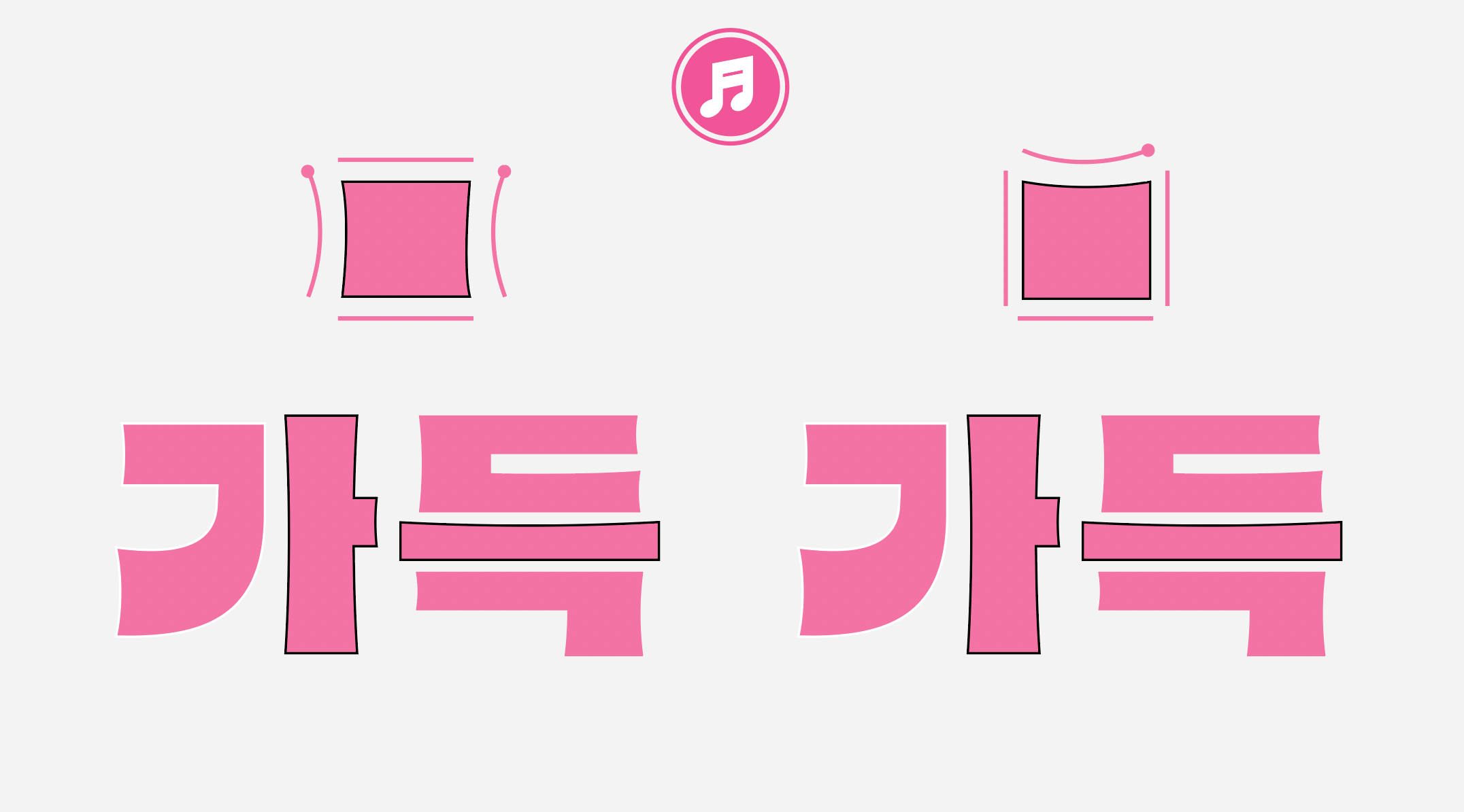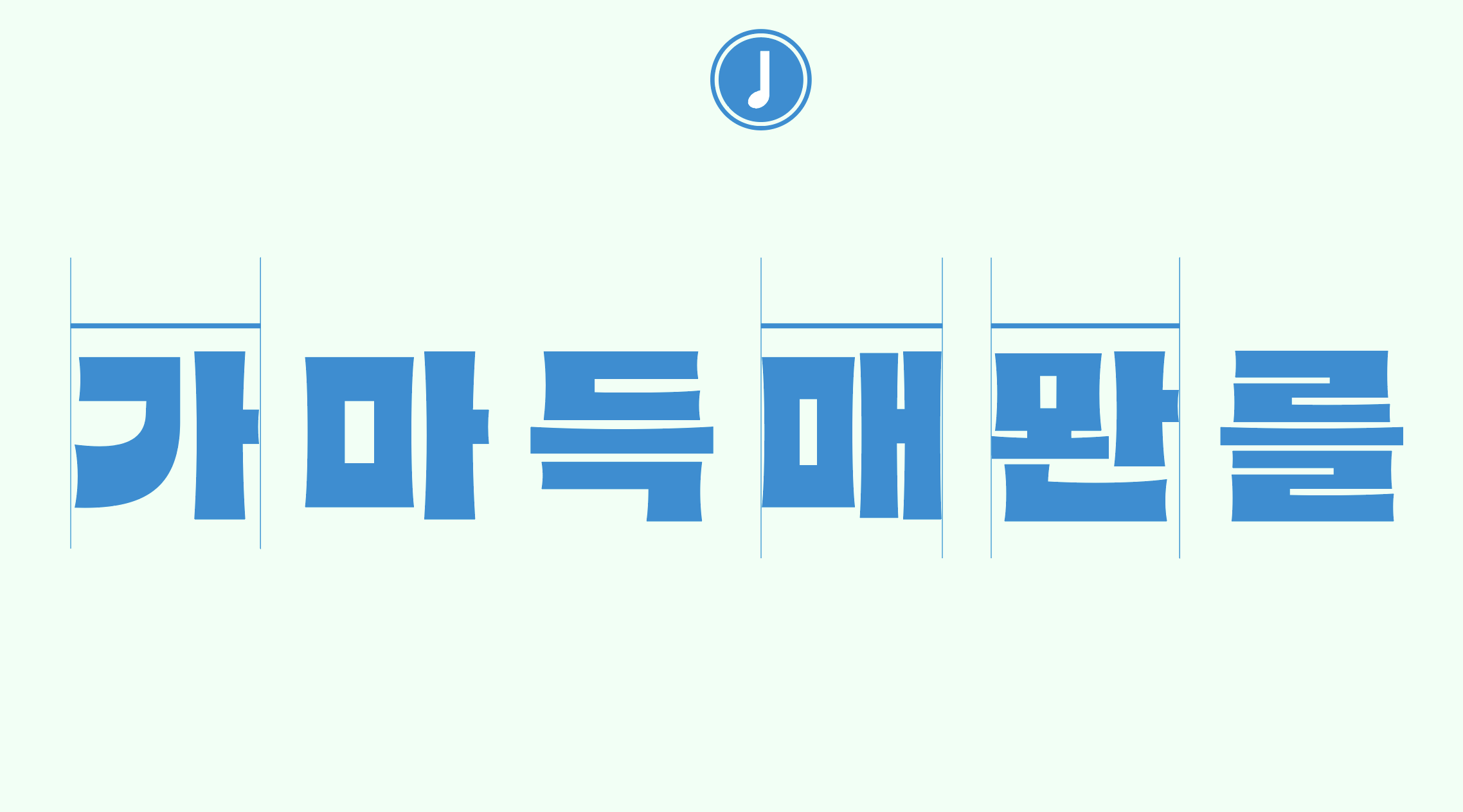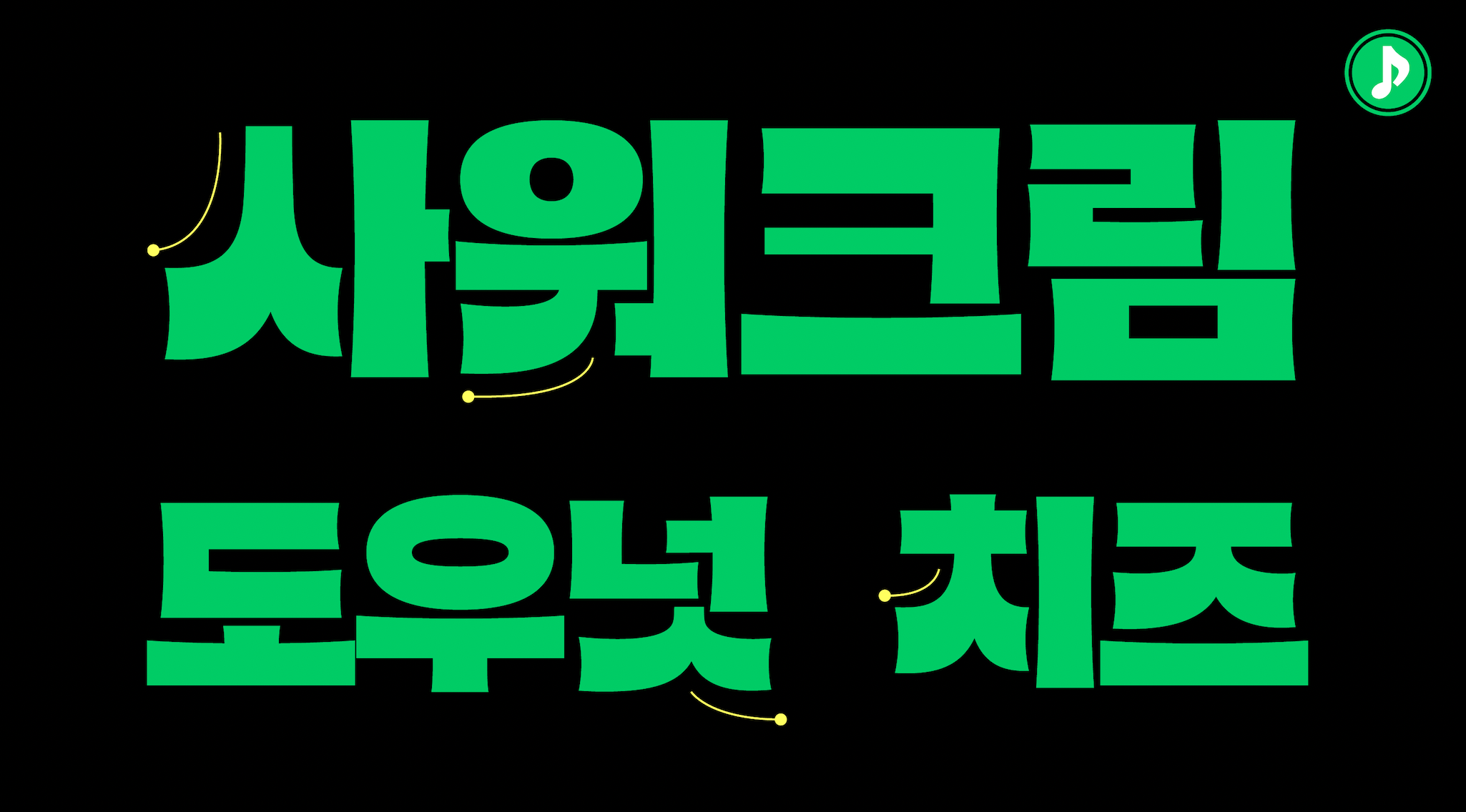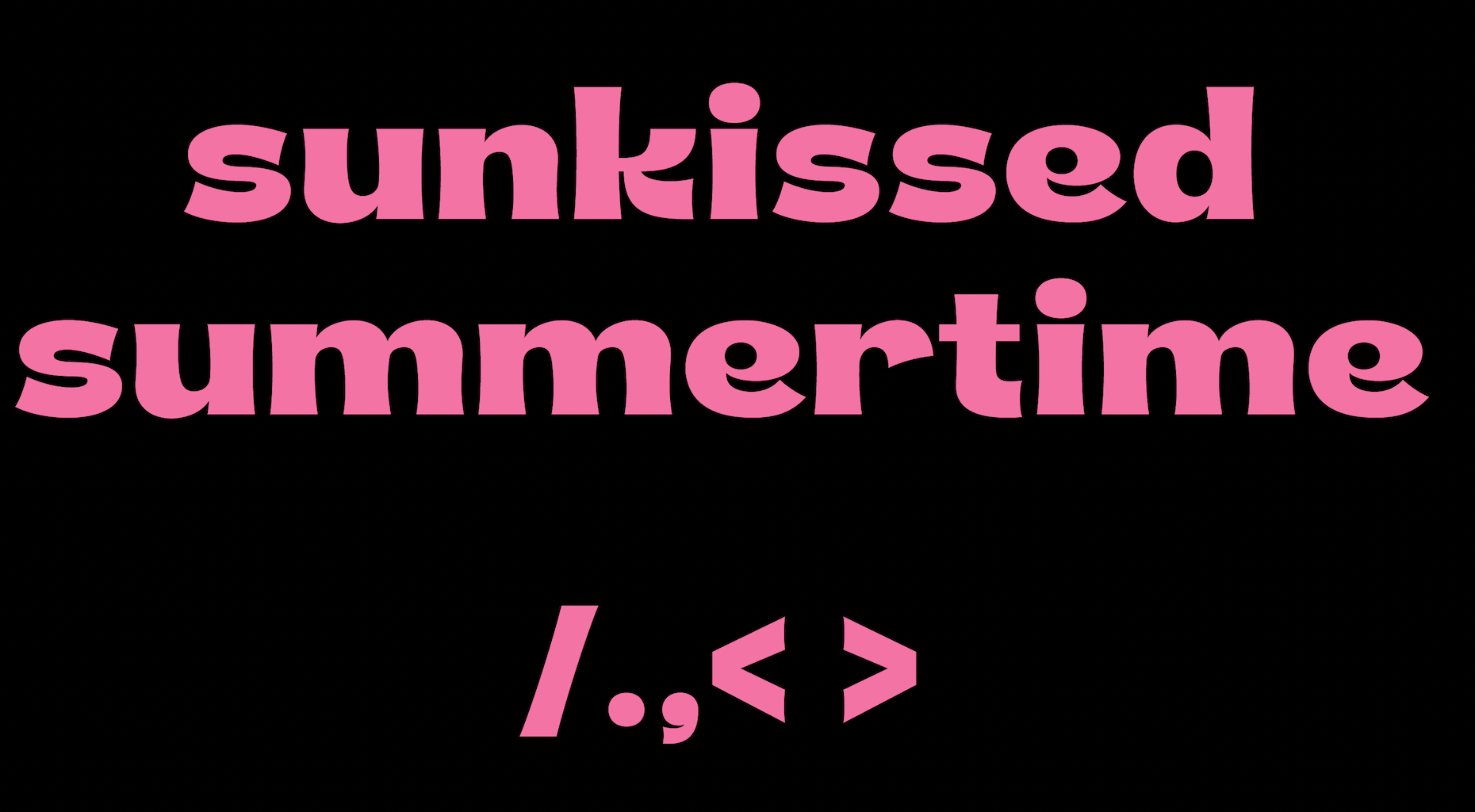
다양한 컨셉으로 활용이 가능하고 독특한 디자인 요소가 많은 서체 시리즈. 개성있는 디테일로 시각적 재미를 더하고 풍부한 이야기를 담을 수 있는 서체이다.
폰트 설명
J쥬키니는 네모틀 안에 꽉 채운 자소와 두껍고 단단한 획으로 무게감이 느껴지는 헤드라인 서체입니다.
J쥬키니는 강한 주목도와 개성, 트렌디함을 보여주는 Black 굵기의 그래픽체로 아주 큰 사이즈에서부터 부제목 사이즈까지 모두 활용할 수 있습니다.
한글 디자인 특징
1. 획: J쥬키니는 오목한 획과 강, 중, 약의 획대비가 흥미롭게 표현된 서체로써 각 모임꼴별 변화하는 획 두께에 주목해 주세요! 특히 민글자에서 받침 글자로 갈수록 획의 강약 대비가 더욱더 강해지도록 모듈화했습니다. 이는 획이 많아지는 글자 안에서 공간의 분배와 획대비의 컨셉을 효과적으로 유지할 수 있으며 동시에 글자끼리 서로 무게감 차이를 최소화할 수 있습니다.
2. 자소디자인: J쥬키니는 개성있는 자소디자인이 특징입니다. ㅅ,ㅈ,ㅊ (ㅆ,ㅉ)의 비대칭 디자인과 ㄱ,ㅋ,ㅟ, ㅝ 과감하게 뻗어가는 곡선 획이 특징입니다.
라틴 디자인 특징
‘ㄱ, ㅅ’의 빗침과 ‘ㅟ’의 짧은 기둥에서 보이는 곡선으로 두껍게 뻗어가는 획을 K,Q,R,에서 표현했고, 전체적으로 강, 중, 약 획대비를 살려 한글과 통일성을 가져갔습니다.
숫자, 약물
한글 디자인의 통일성을 살린 숫자와 기호를 생각하며 디자인했습니다. 숨은 추가글립이 있는데요, 기본형 '&'과 함께 추가로 제작된 개성있는 '&' 도 찾아보세요 :)